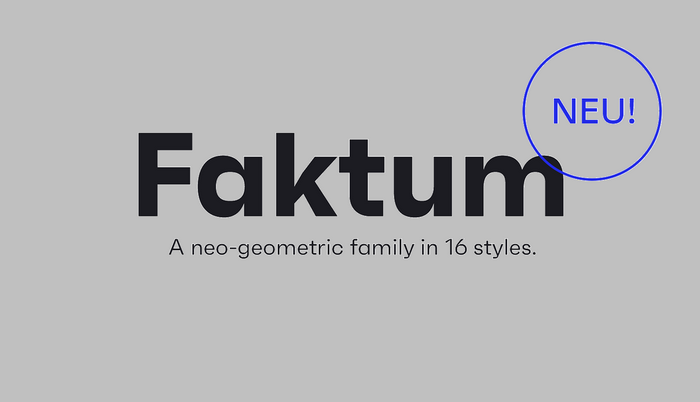
A Faktum Font Family é uma nova família de tipo geométrico sans-serif inspirada na arquitetura e design do segundo terço do século XX. Este projeto inovador apresenta linhas claras, curvas orgânicas e formas geométricas que foram extremamente populares entre arquitectos e designers daquela era. O designer Hamilton explorou essa proposta em seu estilo modernista para criar uma fonte contemporânea e de alta qualidade. Esta família de tipos não apenas é uma releitura do passado, mas também transmite um forte sentido de atualidade, adaptando-se perfeitamente para ambientes digitais atuais. Seja você designer ou arquiteto, o Faktum Font Family é uma escolha inteligente que reflete a evolução constante e moderna da arquitetura e design. Composta por 14 fontes diferentes, incluindo variáveis e personalizadas, esta família de tipos oferece infinitas possibilidades para expressar seu projeto de forma única e profissional.